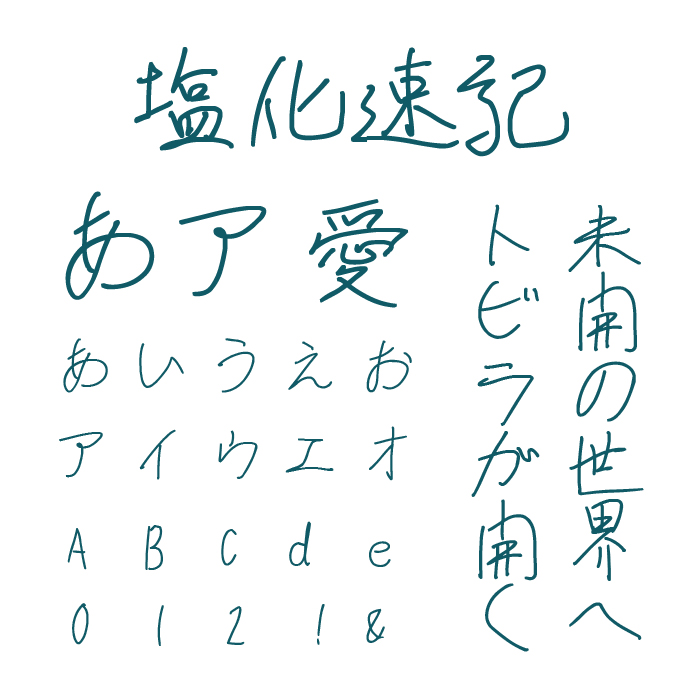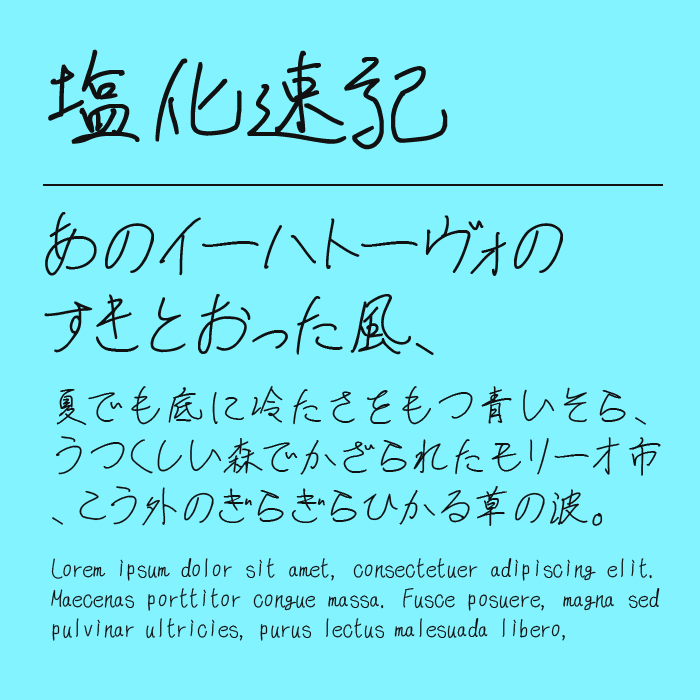
塩化速記フォントは、リズム感のある細筆でラフに描かれたような手書き風フォントです。
少し崩したようなゆるやかに流れる線と、やや跳ねるようなクセのある字形が特徴的で、まるで書き殴ったメモのような奔放さを感じさせる文字です。癖がありながら、日常のつぶやきやラフな文章を表現するのにぴったりなフォントです。
個性的でありながら親しみやすく、イラストの吹き出し文字やZINEのキャプションなどにも映える、ラフテイストが光るフォントです。
収録文字は、漢字・ひらがな・カタカナ・アルファベット・数字・記号が収録。